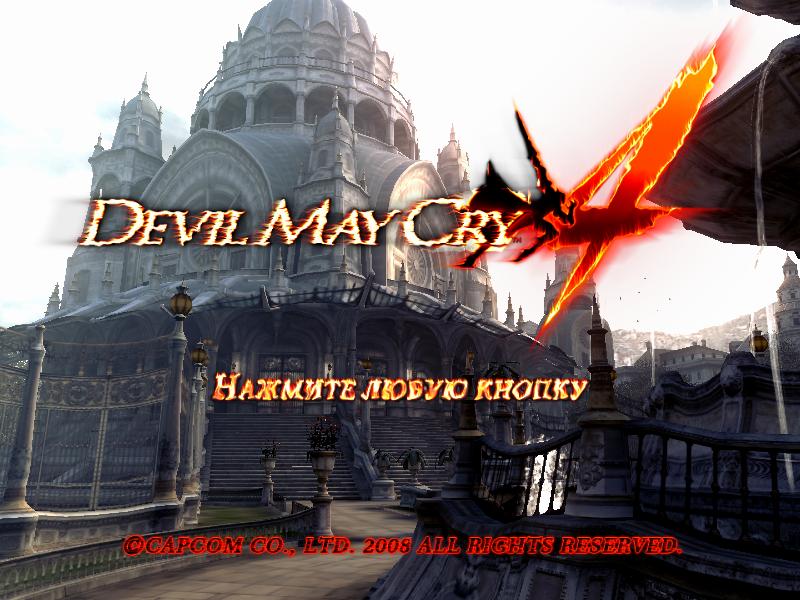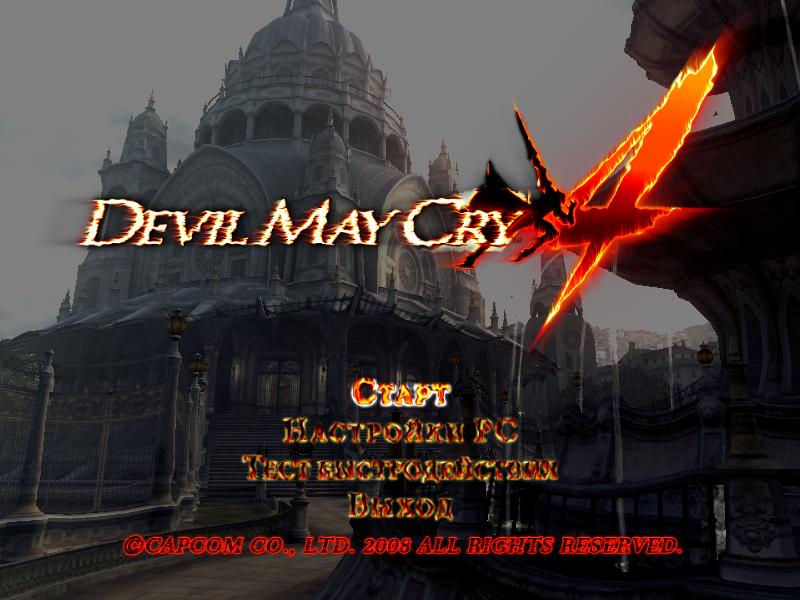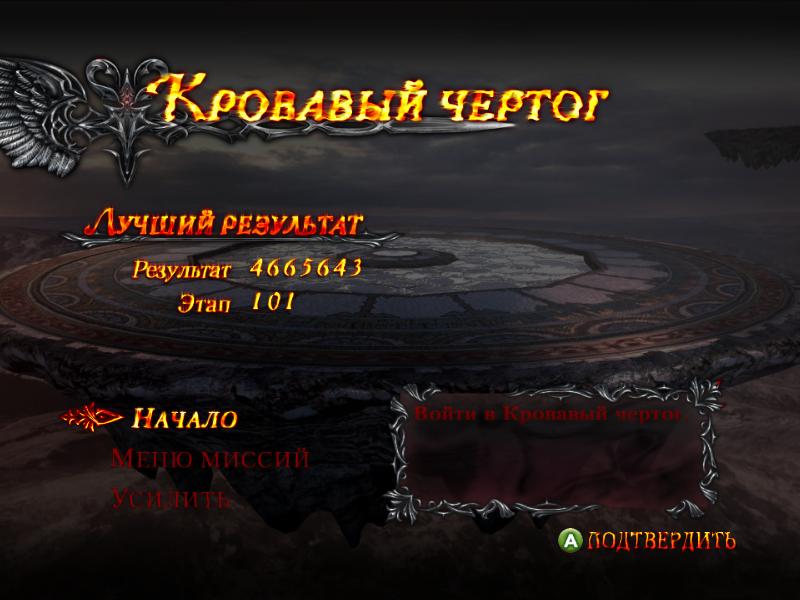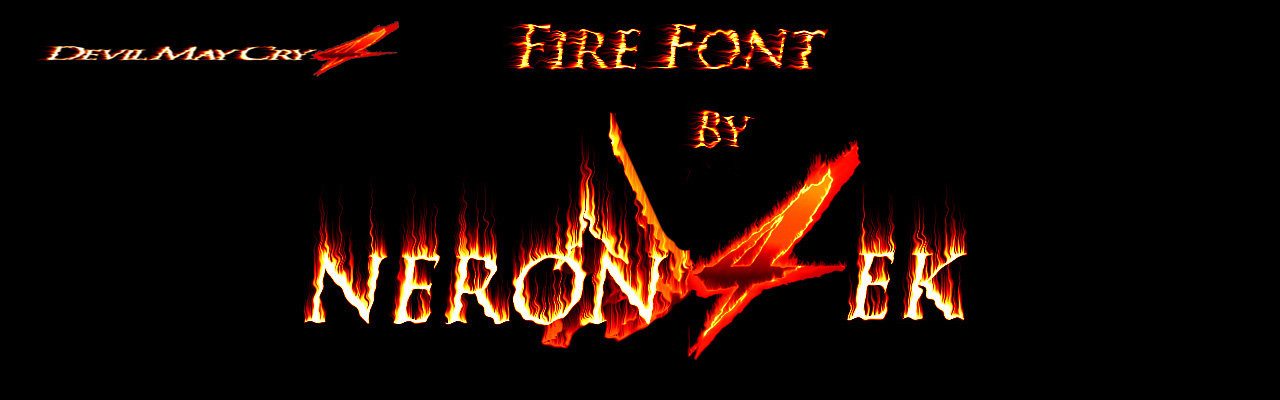
Небольшой мод заменяющий буквы меню игры на "Огненные буквы". Не знаю как мод работает на пиратских копиях игры, но на лицензии от 1C хорошо работает. Русификатор от 1С можно скачать тут
некоторые надписи жестоко пестрят,а так красиво - молодчик +10
NE7, ничего не поделаешь! Красота требует жертв!;)
хорошо сделано а можно зеленого цвета огонь?